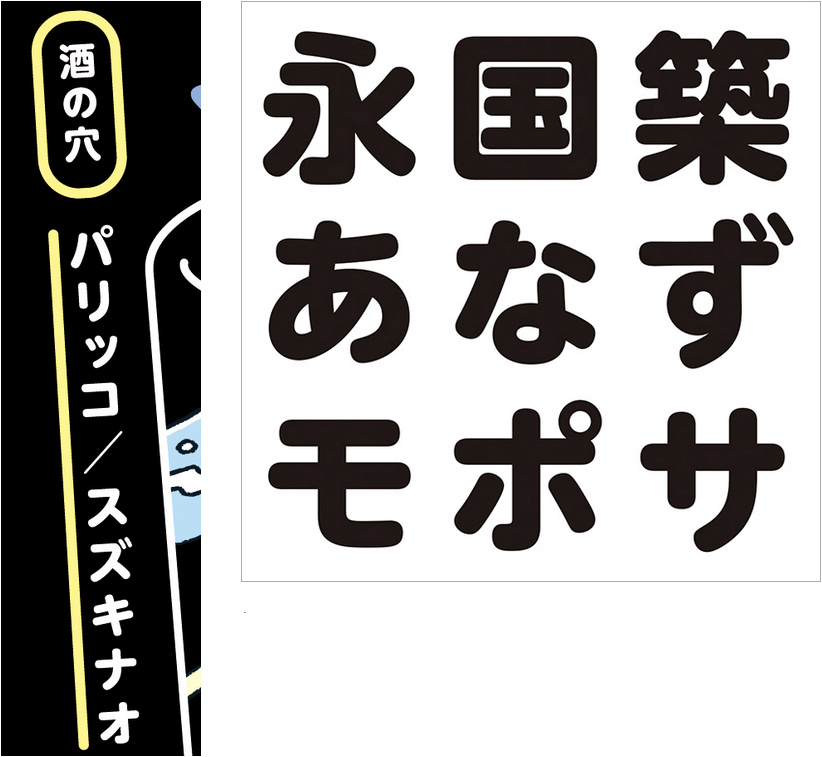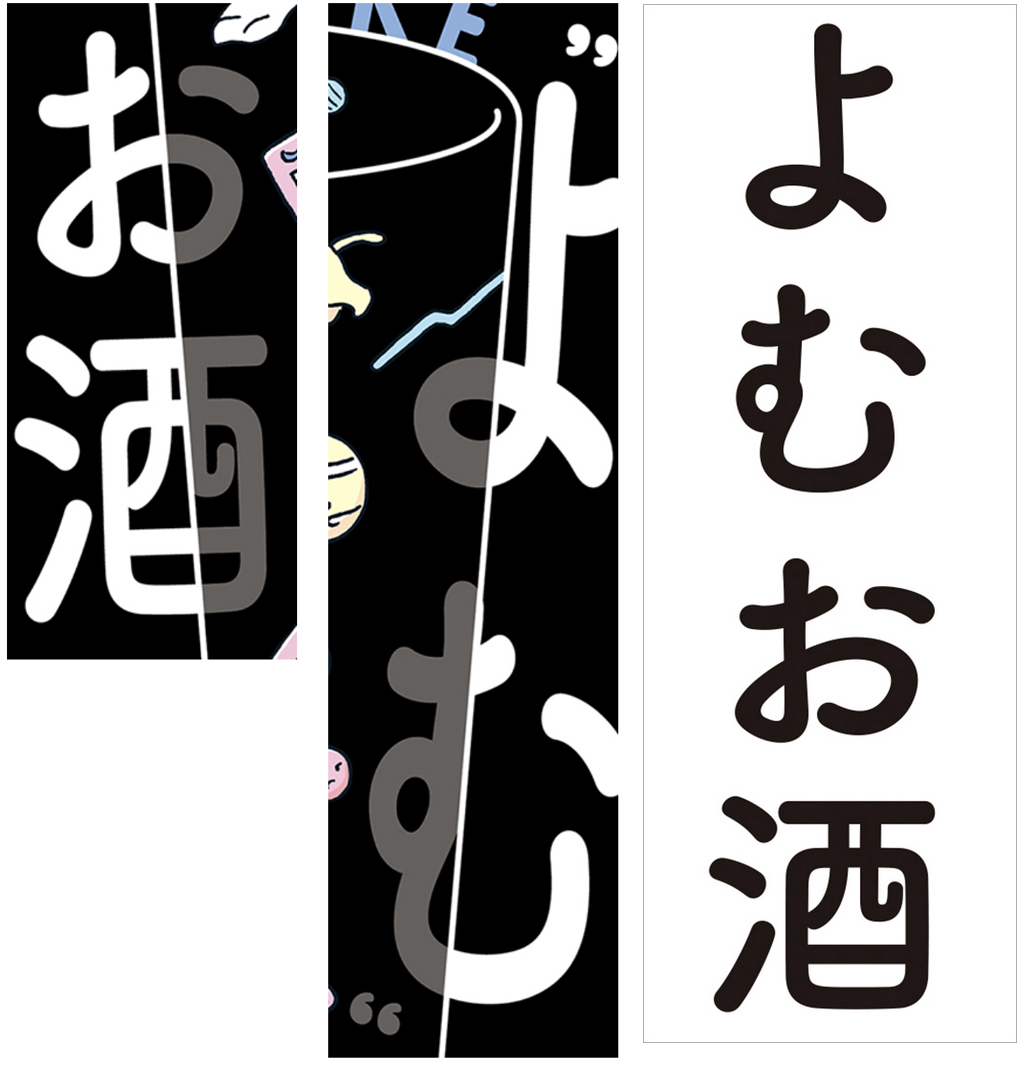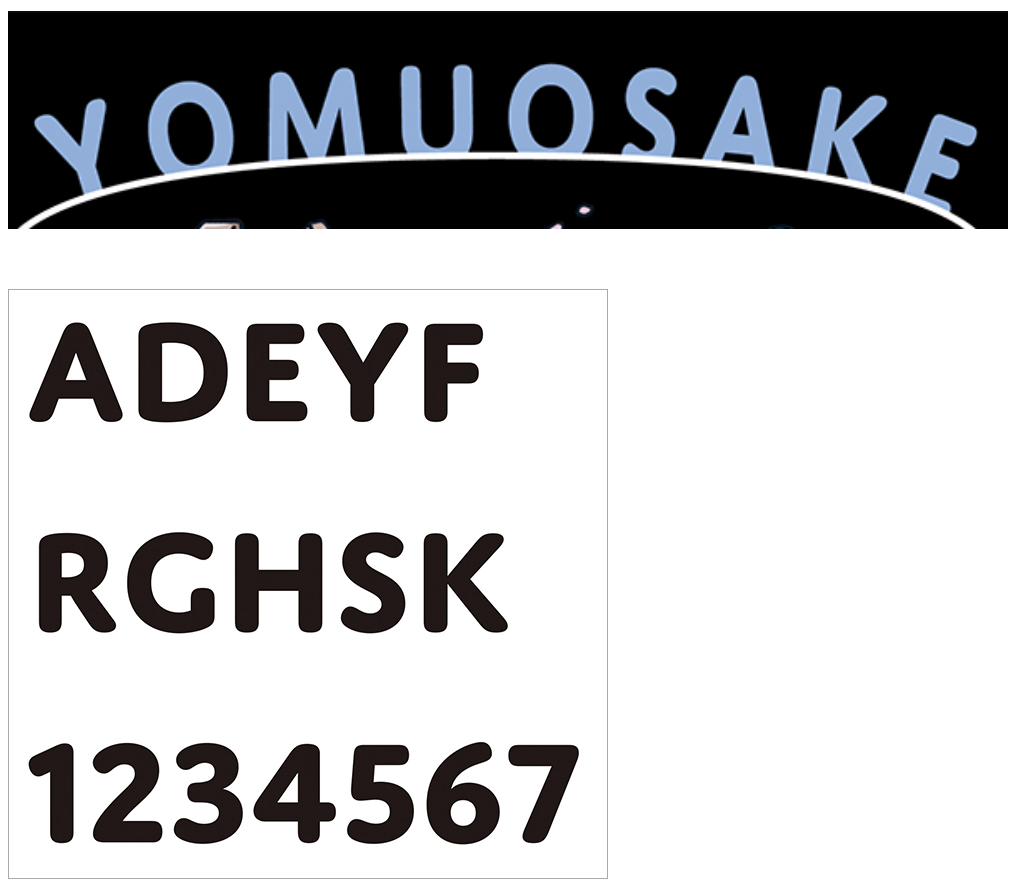
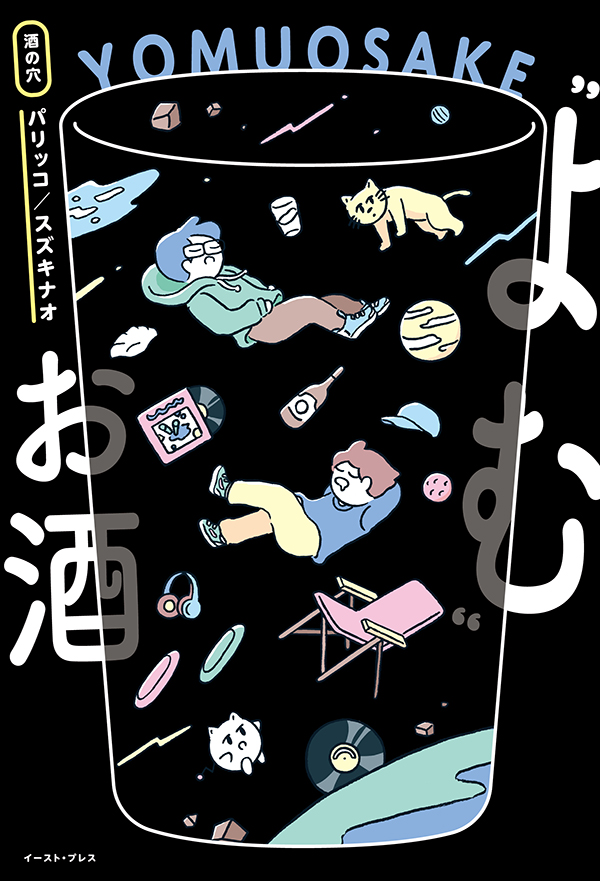
今回は書籍『“よむ”お酒/パリッコ、スズキナオ』の使用フォントをご紹介。本記事はデザイン構成において重要な「フォント」の選定プロセスや加工方法を、貴重なプロの実例から紐解いてデザイン制作に役立てる連載です。
丸ゴシックをベースに使いゆるくて楽しい感じに
人気酒場ライターふたりによる酒飲みユニット「酒の穴」が著した初エッセイ集。「会社の飲み会」や「酒のシメ問題」「粋な飲み方」など、酒にまつわるあれこれがゆるーく、ぬるーく、たまに真剣に書き綴られている。表紙カバーは「お酒の中に広がる宇宙空間」をコンセプトに、ほんわかしたタッチのイラストやタイトル文字で、著者ふたりのゆるくて楽しい雰囲気が表現されている。
Font.01「筑紫A丸ゴシック B」
温かな丸ゴシック体でゆるくて楽しい感じに
著者の人柄や本の内容に合わせてゆるくて楽しい空間を演出するため、文字要素はすべて丸ゴシック系の書体が検討された。そのうちメインタイトルの文字は一般的な丸ゴシック体のデジタルフォントとは一味違う温かで味わい深いラインを持つ「筑紫A丸ゴシック B」(フォントワークス)がベースに。全体のバランスを意識して長体をかけ、読者の目を引くようにレイアウトされている。
Font.02「JAF Domus Titling Bold」
丸みのある文字でPOPかつスマートに
タイトルのローマ字表記部分は、伝統的なローマン体の骨格をベースにしたラウンド系のサンセリフ体「JAF Domus Titling Bold」(Just Another Foundry)。POPな雰囲気を出すため、メインタイトルと相性がよく、丸みがありつつもスマートな印象の書体が選択された。
Font.03「UD新丸ゴ H」
メリハリを意識しつつ親しみやすい書体に
著者名や出版社名の文字は、ユニバーサルデザインに配慮した判読性の高い丸ゴシック体「UD新丸ゴ H」(モリサワ)。ここではメインタイトルとメリハリをつけるため、クセの少ないシンプルで親しみやすい書体をチョイス。